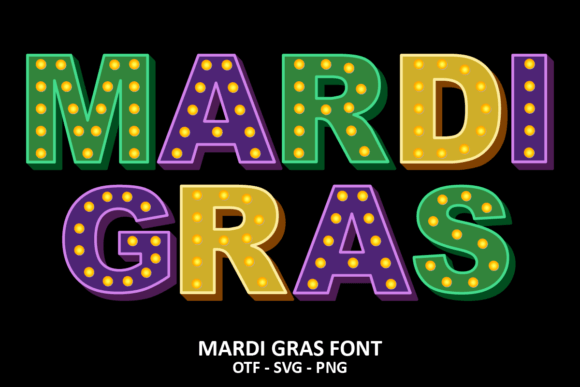
Mardi Gras Font
Mardi Gras Font – خط احترافي مستوحى من أجواء الكرنفال!
أضف لمسة من البهجة والاحتفال إلى تصاميمك مع Mardi Gras Font! يتميز هذا الخط بأسلوبه الفريد المستوحى من أجواء مهرجان ماردي جرا الشهير، مما يجعله مثاليًا للمشاريع التي تحتاج إلى طابع مرح وجذاب.
???? مميزاته:
✔ تصميم إبداعي مستوحى من أجواء الاحتفال
أطلق العنان لإبداعك واجعل تصاميمك تنبض بالحياة مع Mardi Gras Font! ????✨